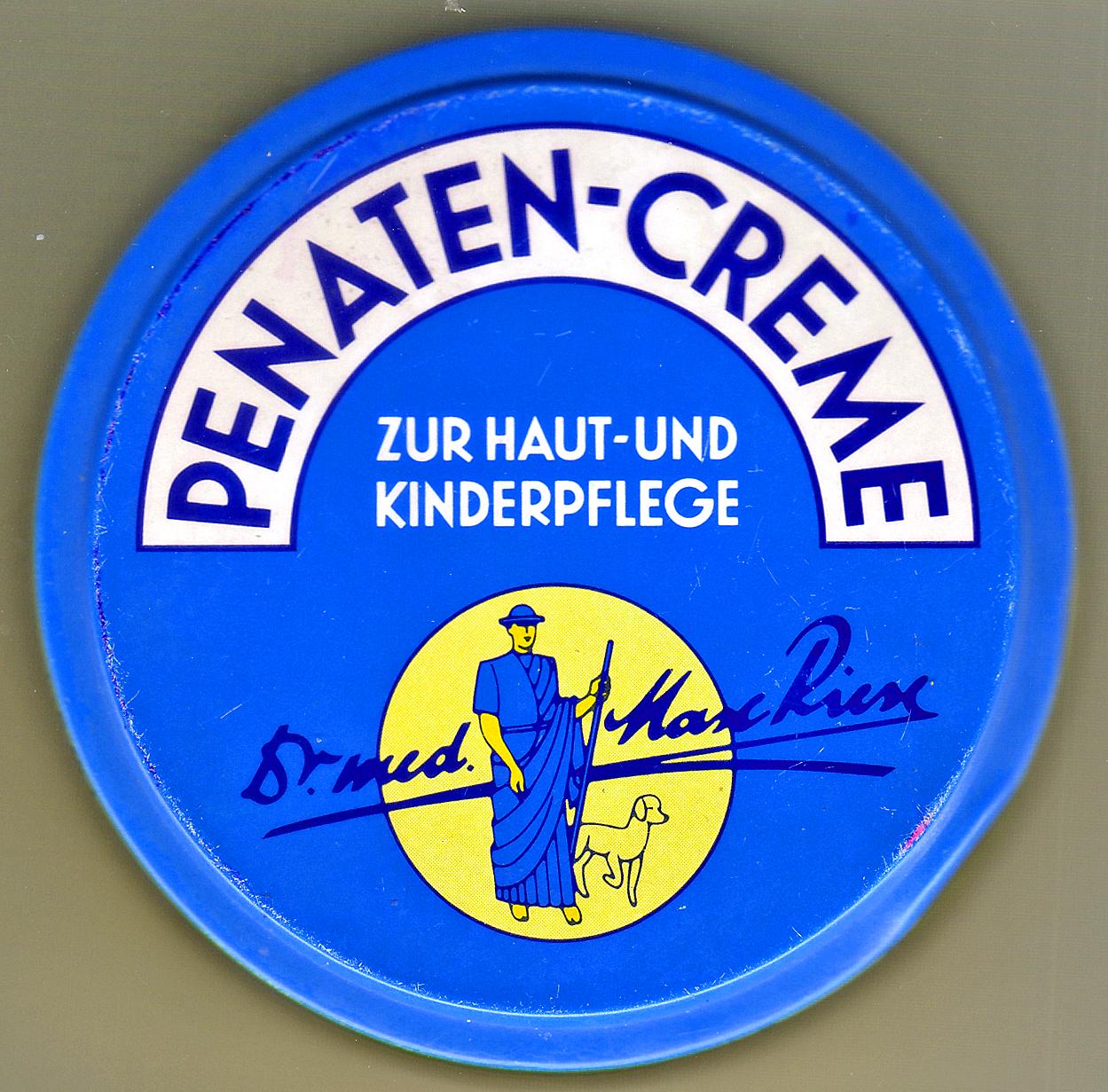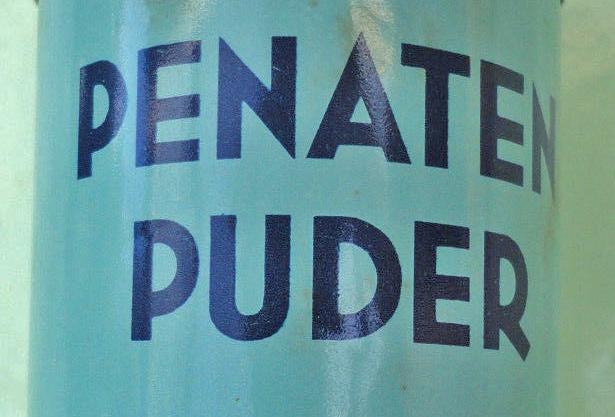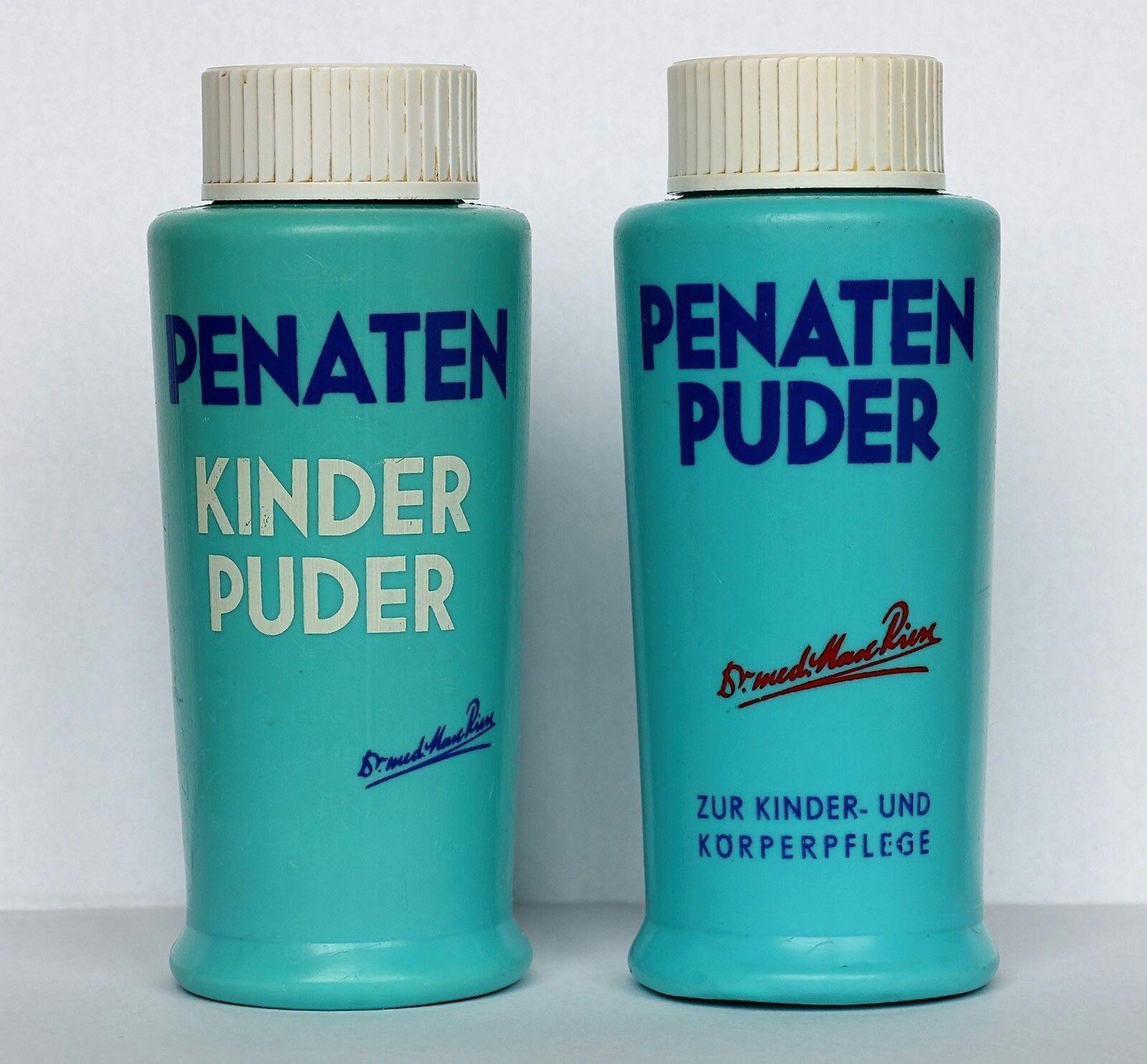
Frühere Hausschrift von PENATEN gesucht!
Auf meiner schon etwa 25 Jahre alten Penaten-Dose fasziniert mich seit Jahrzehnten der Schriftzug "PENATEN-CREME" sowie der Untertitel "Zur Haut- und Kinderpflege". Die gleichen Grotesken können es aber nicht sein (siehe "R").
Das große "G" bei "Kinderpflege" könnte aus der Erbar-Grotesk sein, denn der waagerechte Strich ist schräg. Wo gibt es das sonst?
Die spitzen Enden bei "N" oder "M" ("Penaten) könnten aus der Kristall-Grotesk (Rund-Grotesk) stammen, das "R" bei "Creme"
widerspricht dem aber.
Ich bitte um Hilfe durch ebenso Grotesken-Verliebte wie ich!
Auch dicht dran und vermutlich sogar die Basis für den Schriftzug auf der Dose: Futura LT (da lässt sich gerade kein Schriftmuster generieren)
Näher drann ist die Bahnhofsfutura von Paul Renner, entwickelt um 1924. Die Bundesbahn hat diese früher für Gebäude benutzt. (*) Durch eine Bildersuche auf Google findet man Beispiele:
BahnhofsFutura (2002) (a modification of Paul Renner's Futura as used in West-German railway stations from 1950-1980: Deutsche Bundesbahn).
Eine Digitalisierung der Bahnhofsfutura gibt es hier:
Bei der Bildersuche werden einem dann auch noch andere Schriften gezeigt, welche ähnlich sind. Beispiel Neutraface/Neutratext.
Wikipedia weiß allerdings nicht sehr viel zum Thema Penaten-Creme, hat aber einige Abbildungen der Dosen:
Aucvh noch einige Dosen, aber in geringer Auflösung:
Die gezeigte Dose sollte aus den 1980ern sein ...
Zum einen glaube ich aber nicht, dass es eine "Bahnhofsfutura" gab. Ich habe mir die alten Schilder ganz genau angesehen. Die Bahn ja ja ausschließlich Majuskeln gebraucht. Sie ähneln extrem der Futura von Paul Renner, weisen aber minimale Schönheits-Veränderungen auf. Sie ist insgesamt fetter als die Buchschrift, aber trotzdem mit spitzem "M" und "N". Teilweise sieht man diese Schilder noch heute, wenn sie nicht ersetzt wurden. Also: Die alte Hausschrift der DB muss anders heißen. Wahrscheinlich wurde sie extra angefertigt.
Zu PENATEN. Nun habe ich nochmals nach alten Schriftzügen gesucht. Leider sind alle oben genannten Grotesken nicht die richtigen. Sie müssen alt sein. Man beachte das besonders schöne schräggestellte "R" bei "PUDER". Ich wüsste nicht, welche Groteske (bei aller Ähnlichkeit) diesen Schnitt anbietet. Auch das "G" bei "PFLEGE" ähnelt eher an Jakob Erbars Grotesk.
Vielleicht muss man hier einfach akzeptieren, das diese alten Packungs-Designs aus einer Zeit vor digitalen Schriften, Stuck für Stück von Grafikern in relativ freier Anlehnung an die genannten Schriften aber eben nicht in genauer Übernahme einer benannten Schrift von Hand gezeichnet wurden, Das führt dann eben auch dazu, das die Schrift von Artikel zu Artikel zwar hinrechend ähnlich ist, um die Marke wieder zu erkennen, aber selten Deckungsgleich ist.
Das war einfach, selbst zu Zeiten der Letraset-Anreibebuchstaben, die schnellste Vorgehensweise, und möglicherweise hatte der Verpackungs-Designer nicht einmal eine Vorlage der Schrift am Arbeitsplatz und hat das schlicht nach der Erinnerung gezeichnet, wie ich es auch bei vielen meiner selbst gestalteten Schriften mache.
Schriften, wie die von Nivea und Penaten waren damals (in den 1920er Jahren) sehr modern. Zuvor auf Nivea und Penaten-Dosen eingesertzte Jugendstil-Formen jedoch gänzlich aus der Mode. Die Schrtiften mit den sehr spitzen A, M, V und W-Formen sah man aber oft, nicht nur auf Creme-Dosen, sondern auch im Straßenbild der Einkaufsstraßen der Großstädte. Schaut man sich Filme und Fotos, die das Leben der Großstadt zeigen mit offenen Augen an, und achtet hier auf abgelichtete Plakate, Werbeanschriften an Verkehrsmitteln oder Ladenschilder (das habe ich mir sehr angewöhnt, ich achte oft dar nicht mehr auf das eigentliche Motiv) dann sieht man diese Schriften recht oft.
Und in den allermeisten Fällen war das eben Handarbeit.